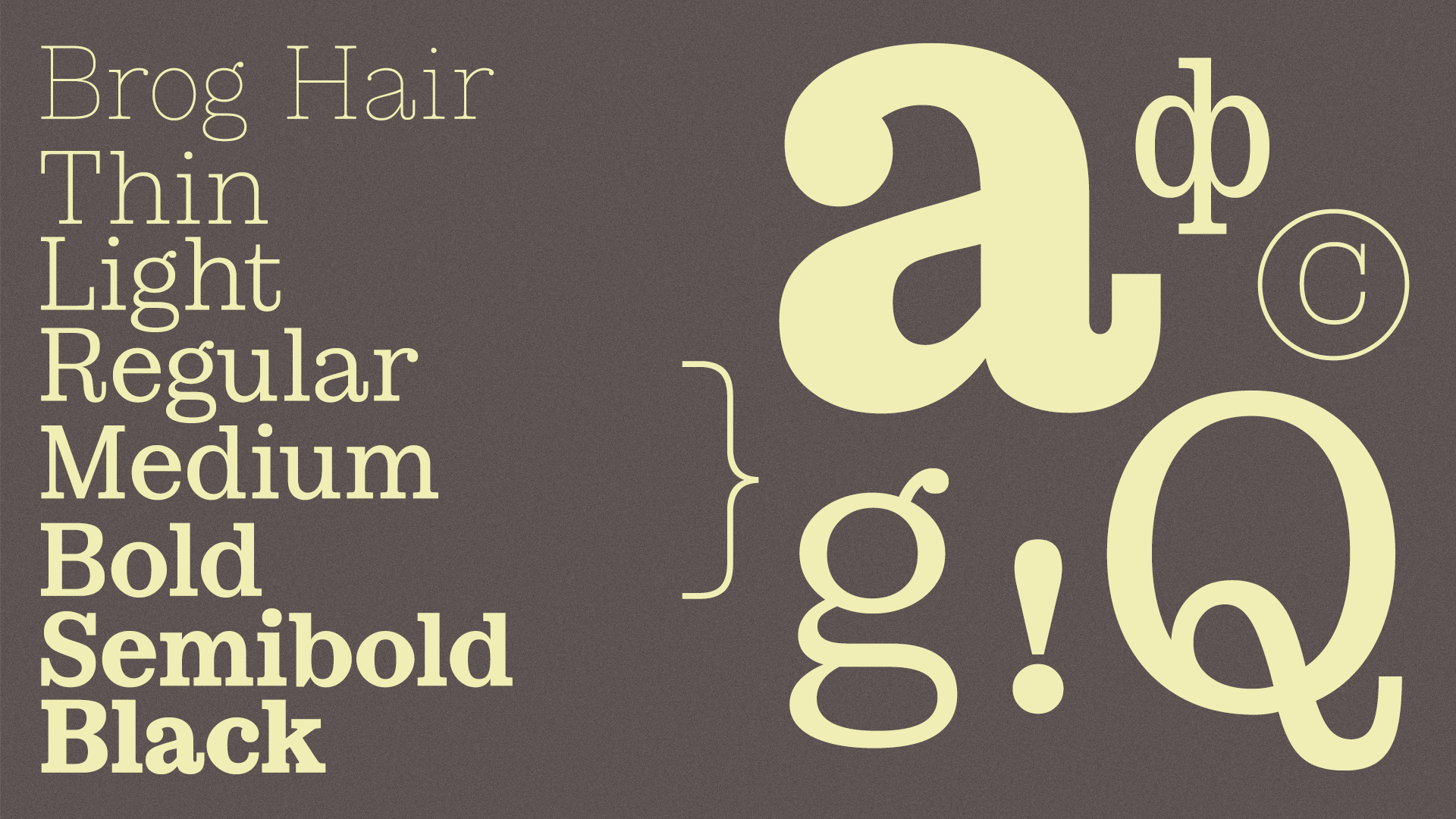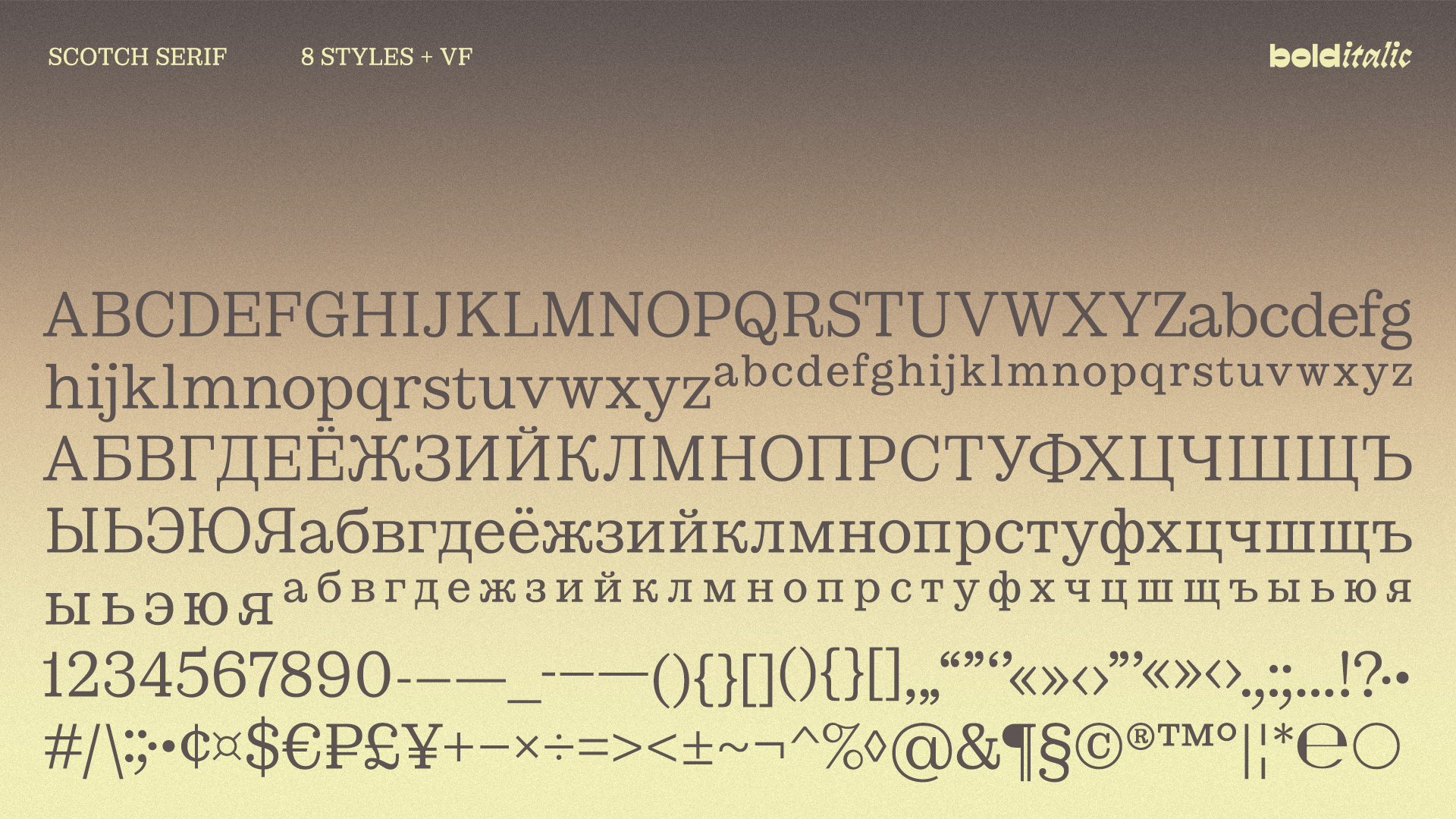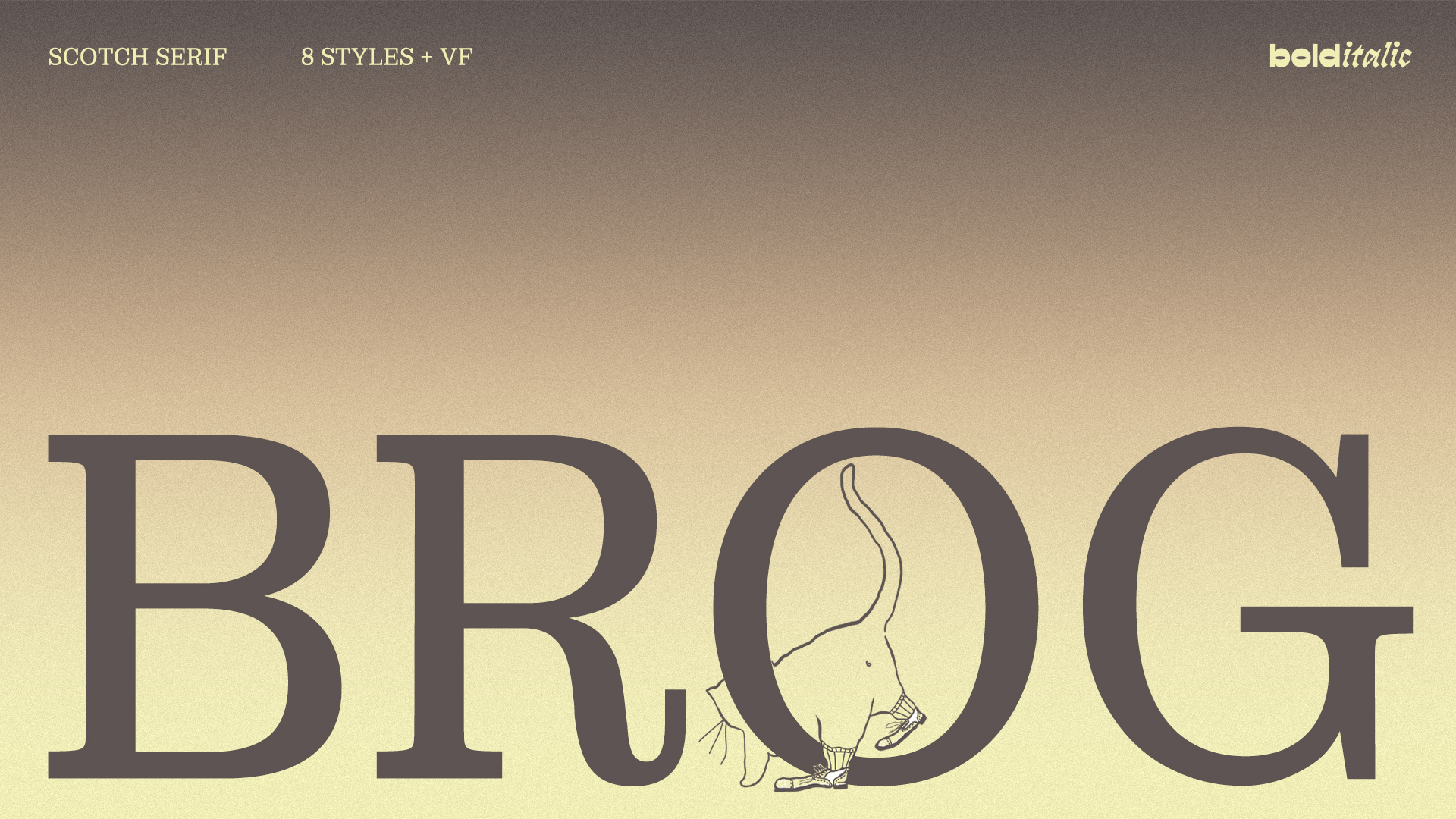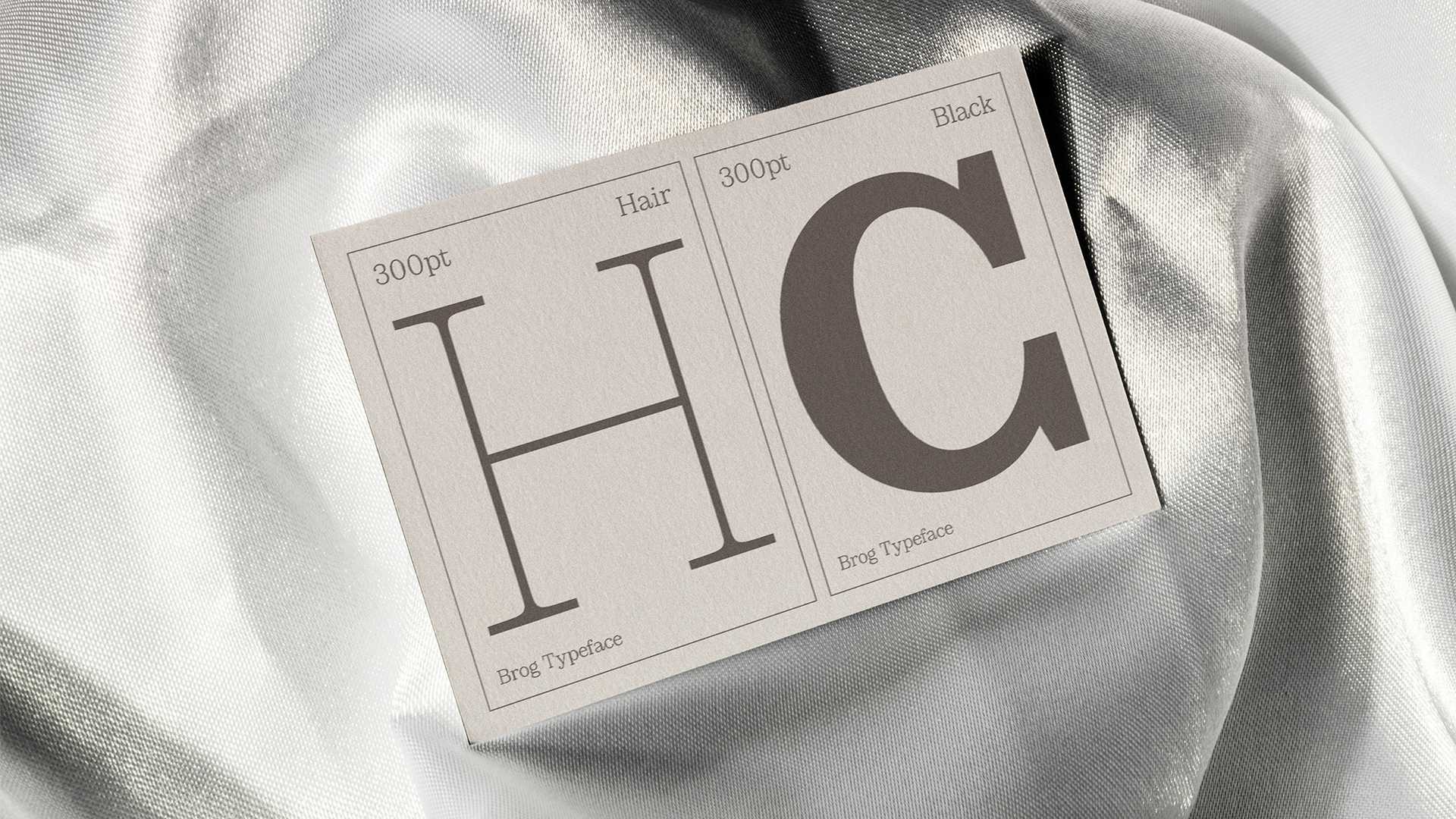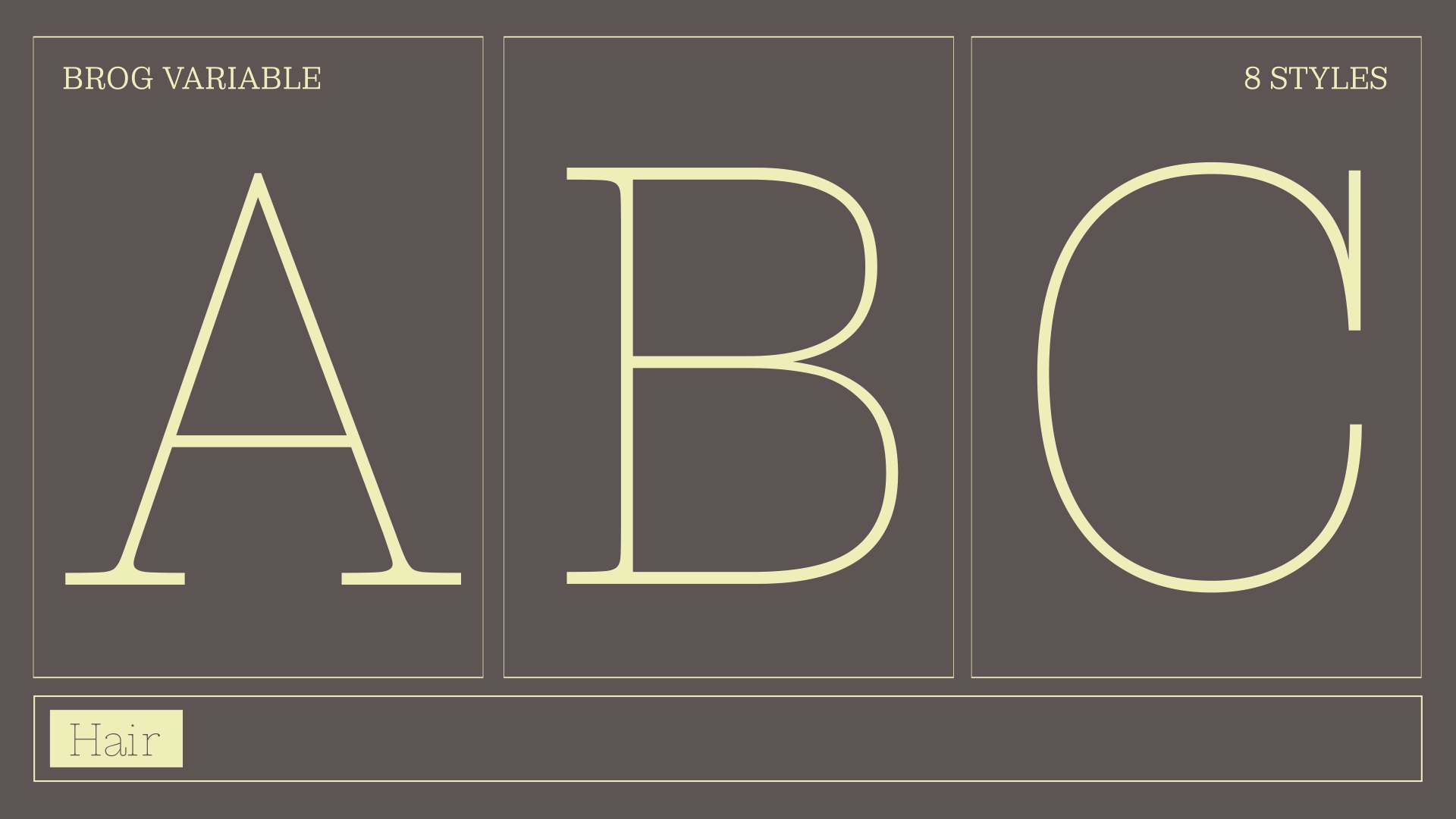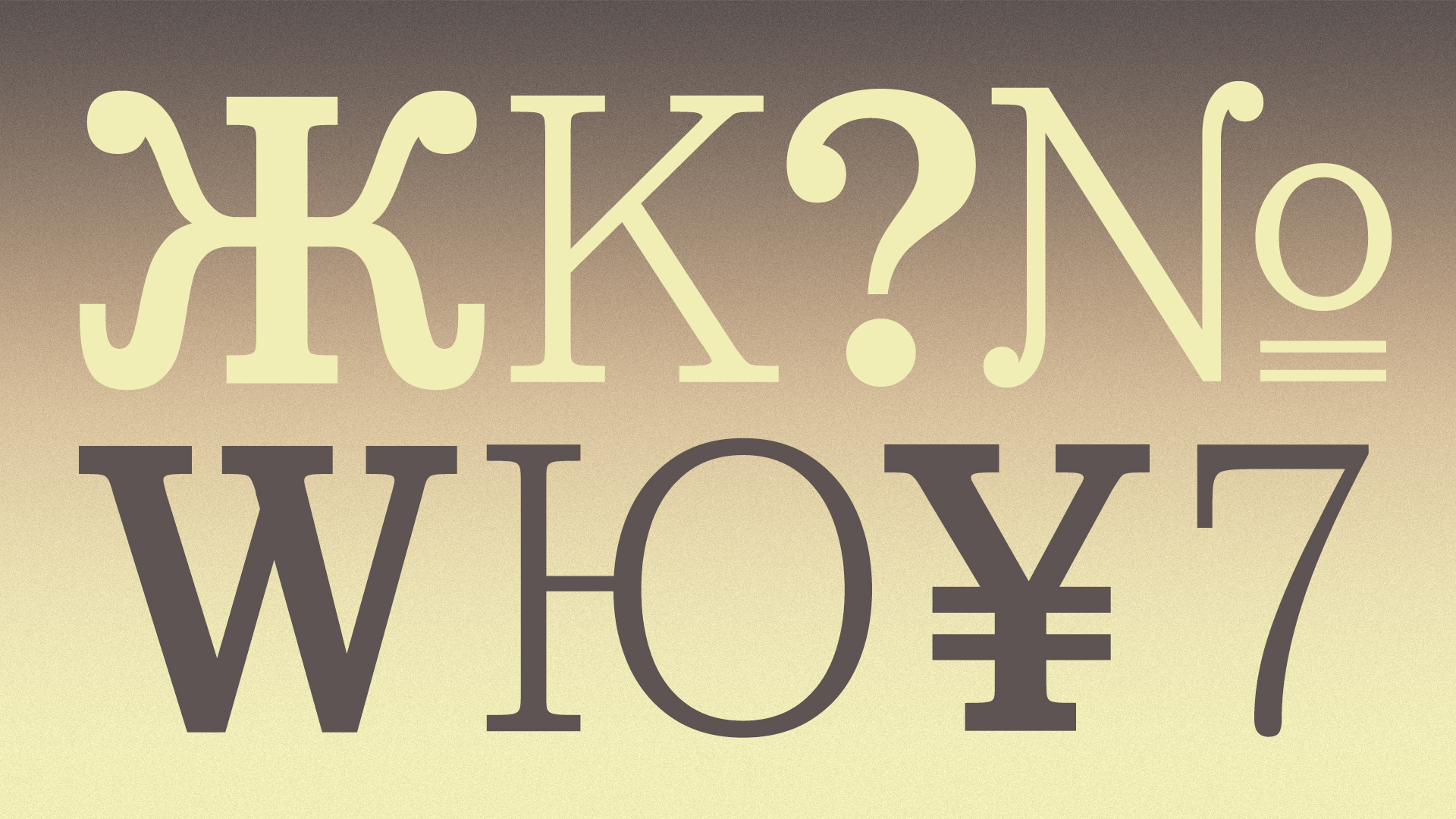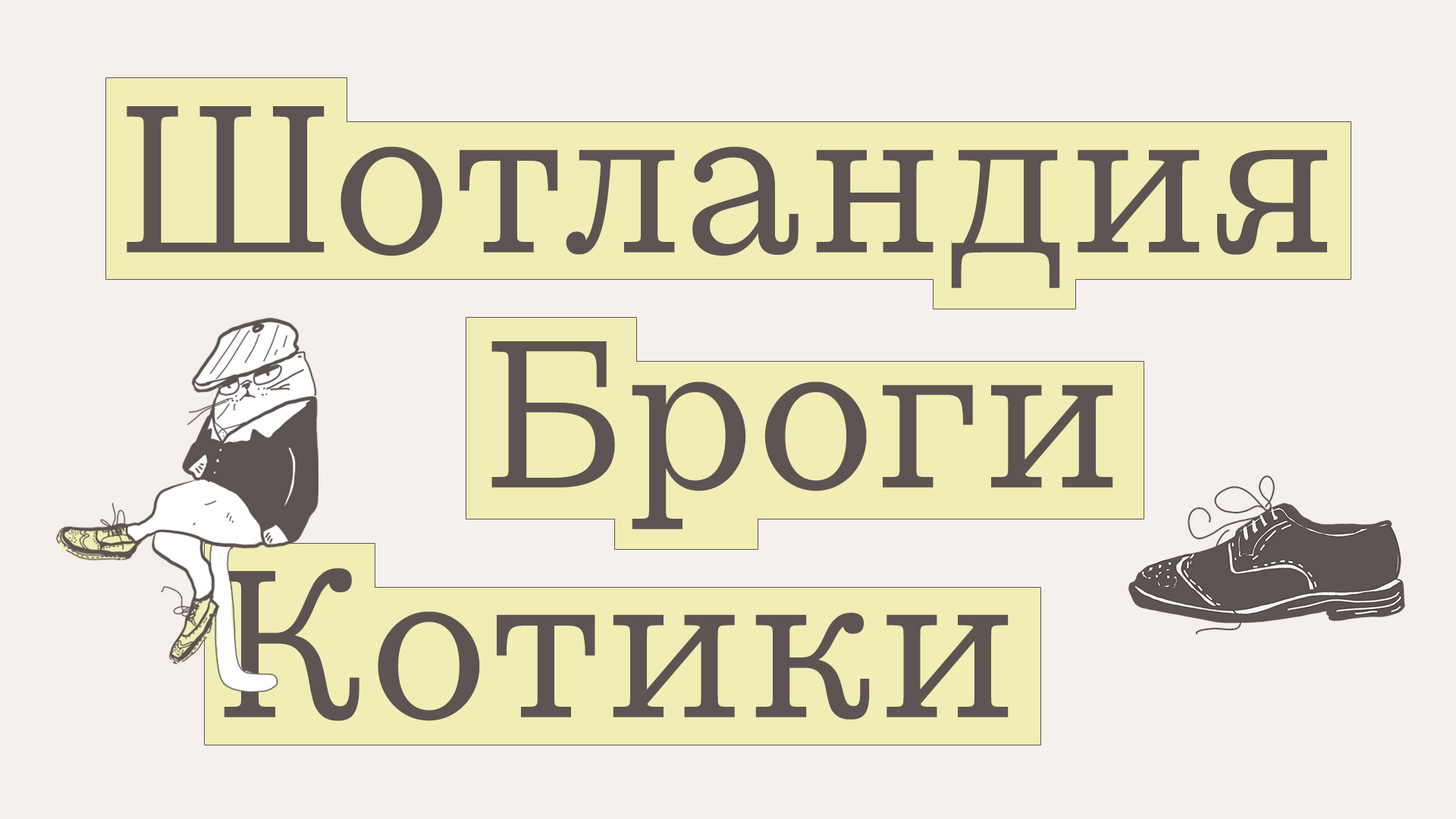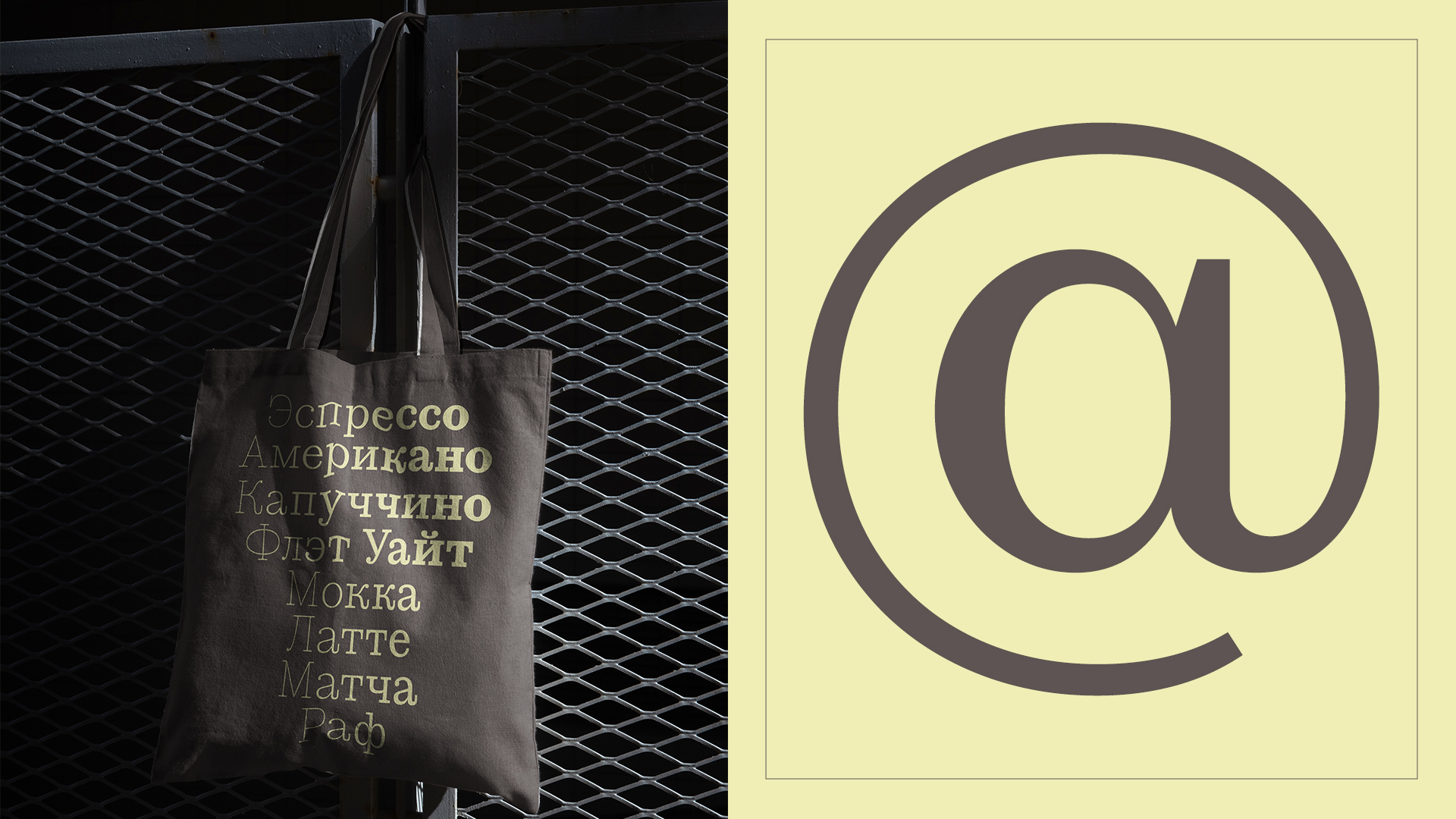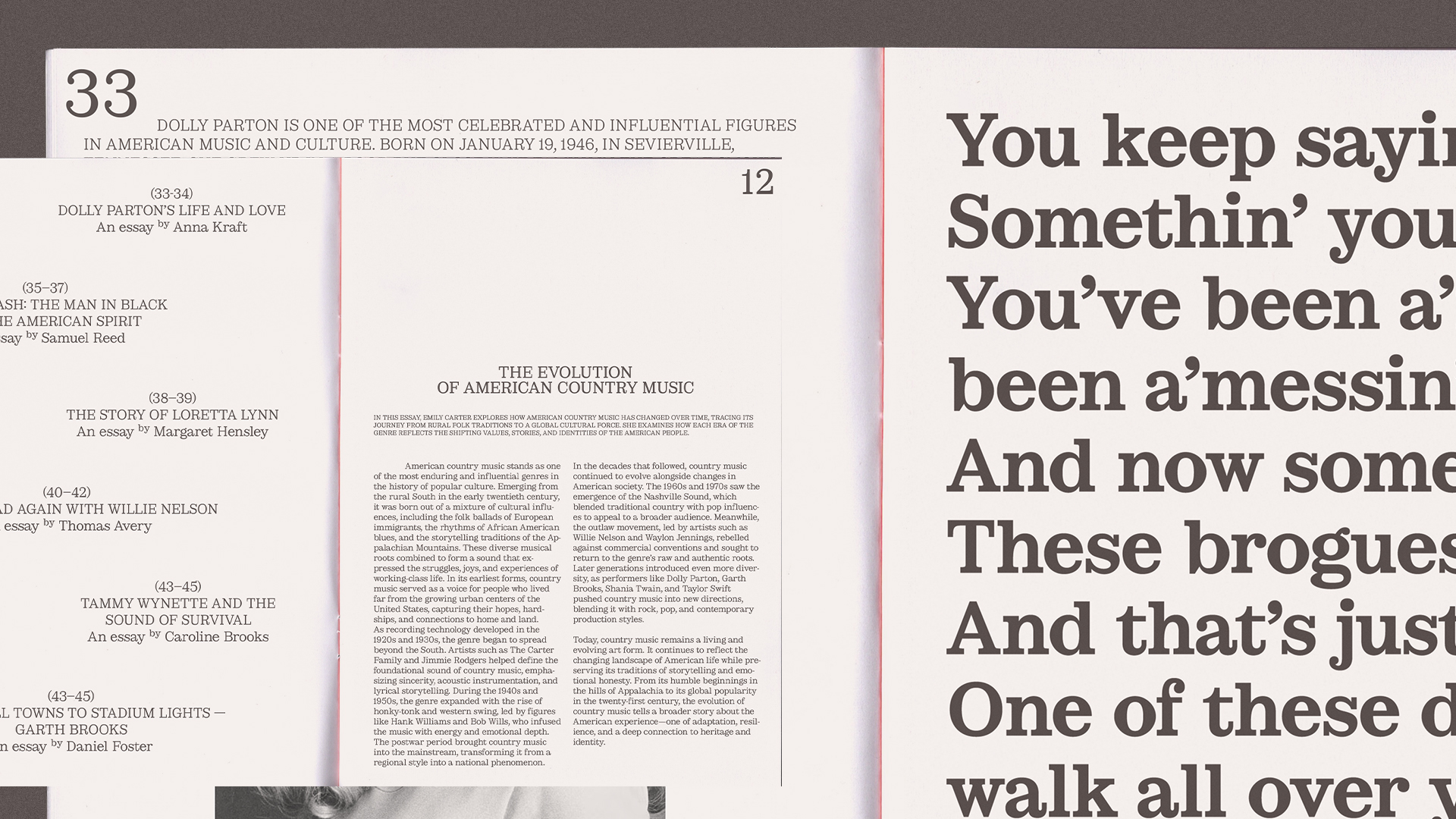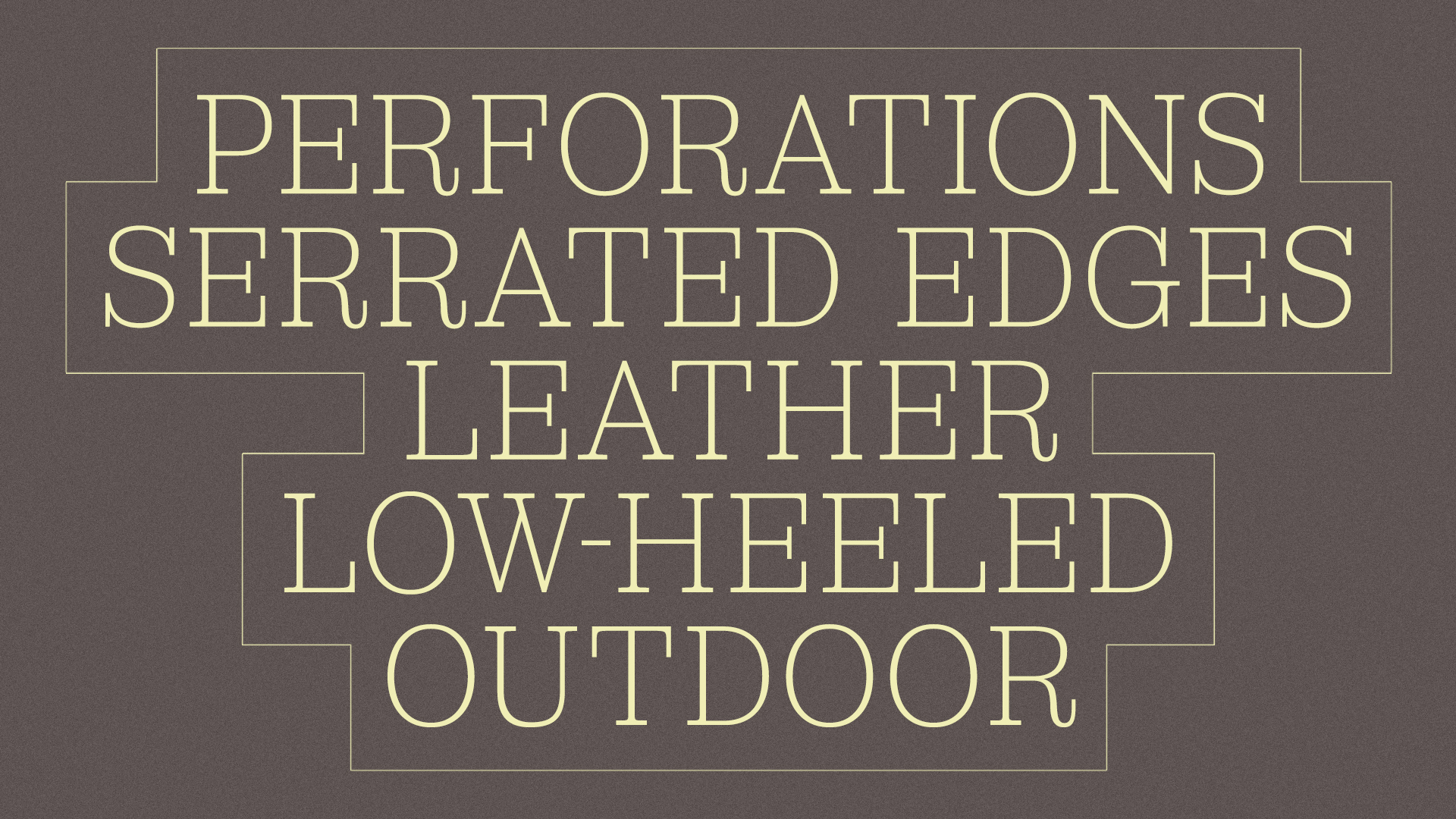
Brog
Современная интерпретация шотландской новостильной антиквы, созданная для универсального использования. Шрифт отличается широкими засечками и закрытыми апертурами.
Брог вариативен по насыщенности, обладает довольно большим диапазоном. Шрифт уверенно работает и в крупном, и в мелком кегле, что позволяет его применение на самых разнообразных носителях.